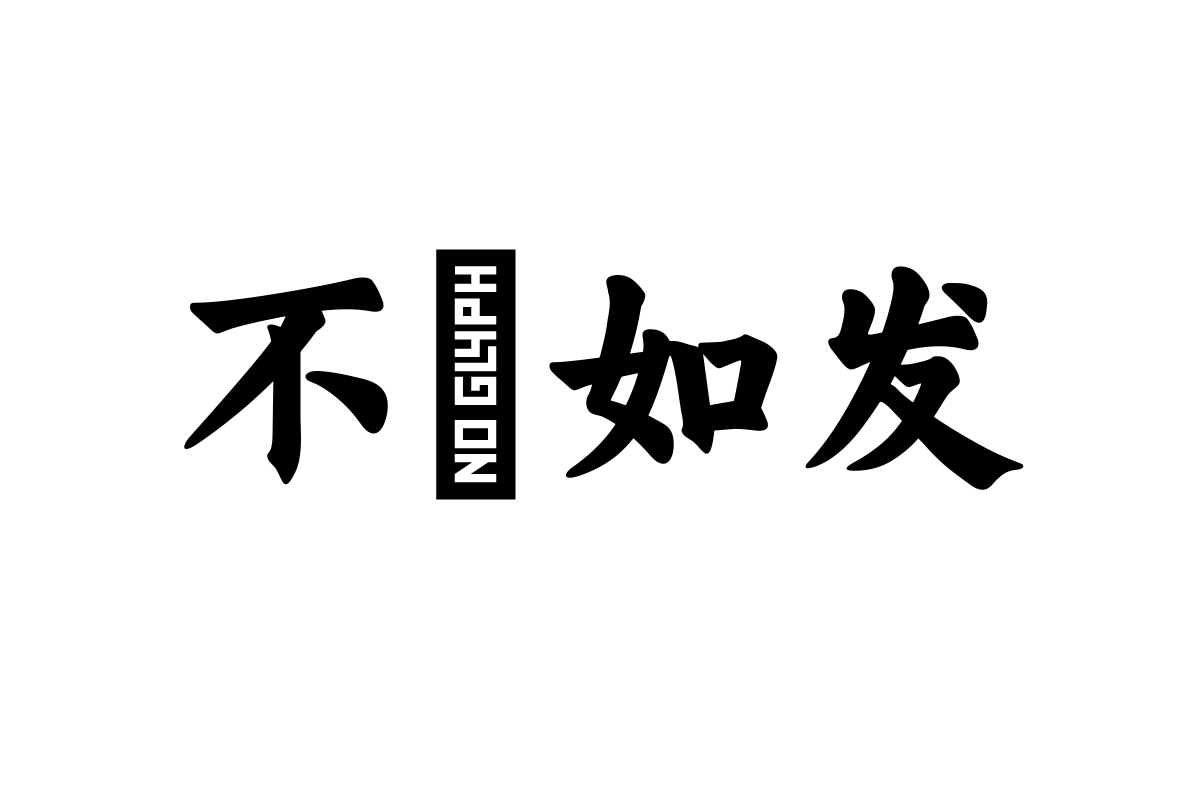
三极榜楷体是一种具有独特风格的中文字体,由著名书法家和设计师张华设计。这种字体以其独特的结构和笔画特点而著称,给人一种简洁、现代的感觉。
三极榜楷体的笔画流畅自然,线条粗细适中,既有传统的楷书韵味,又不失现代感。它的字形结构紧凑,笔画连接紧密,使得整个字体看起来非常协调。此外,三极榜楷体的字形也具有一定的变化,使得整体视觉效果更加丰富多样。
三极榜楷体适用于各种场合的文本排版,如书籍、报纸、杂志等。它的使用不仅能够提高文本的可读性,还能够增加文本的艺术感和美感。同时,由于其独特的风格,三极榜楷体在设计领域也有着广泛的应用,如商标、标志、包装设计等。
总之,三极榜楷体是一种具有独特风格和魅力的中文字体,它以其简洁、现代的特点赢得了众多用户的喜爱。